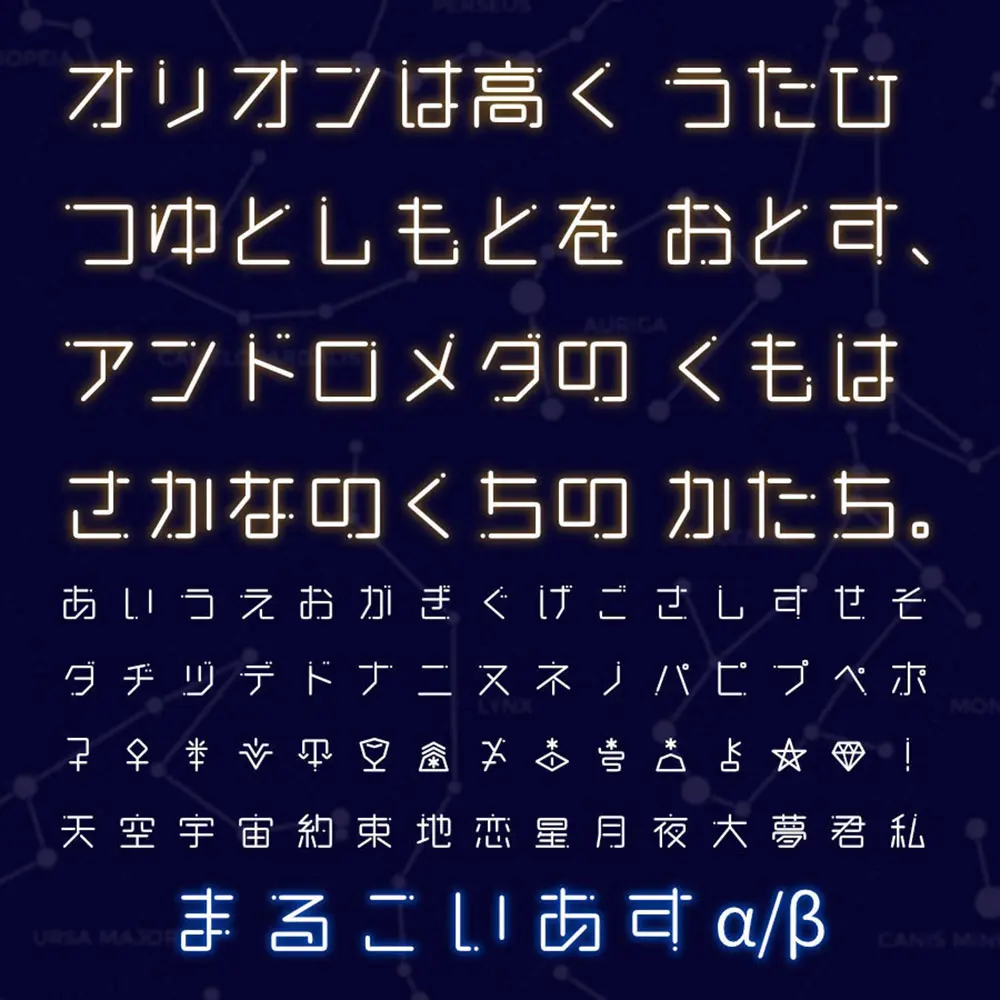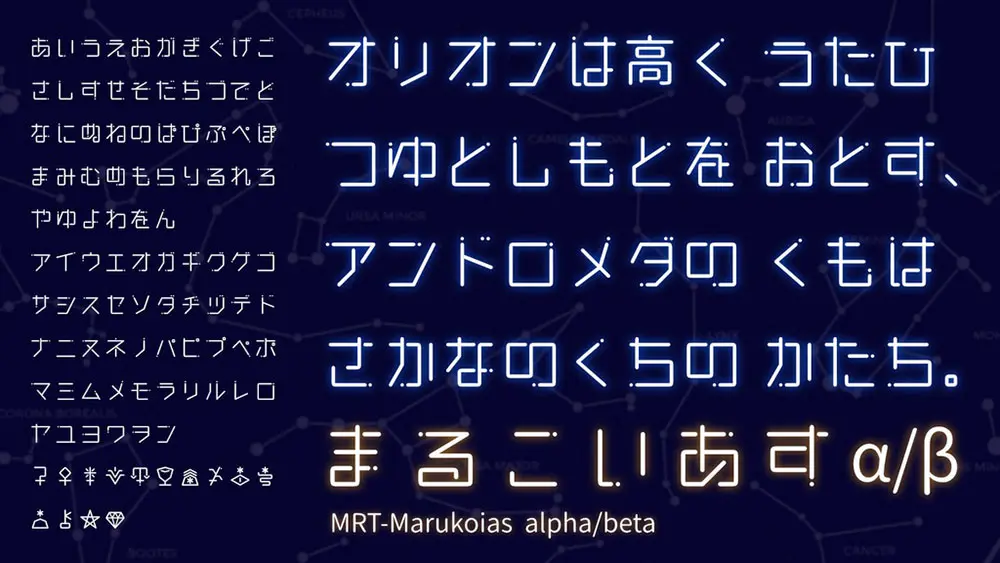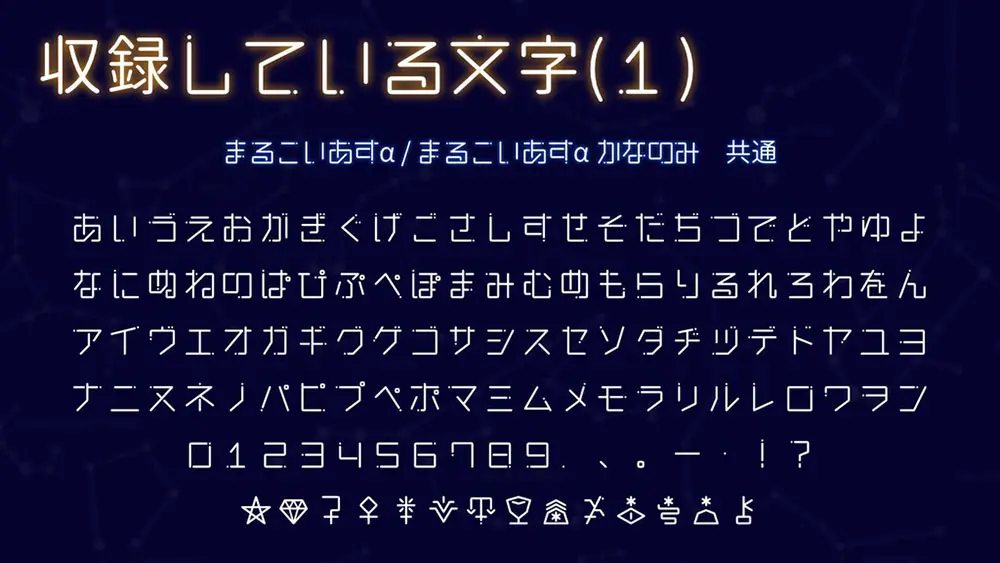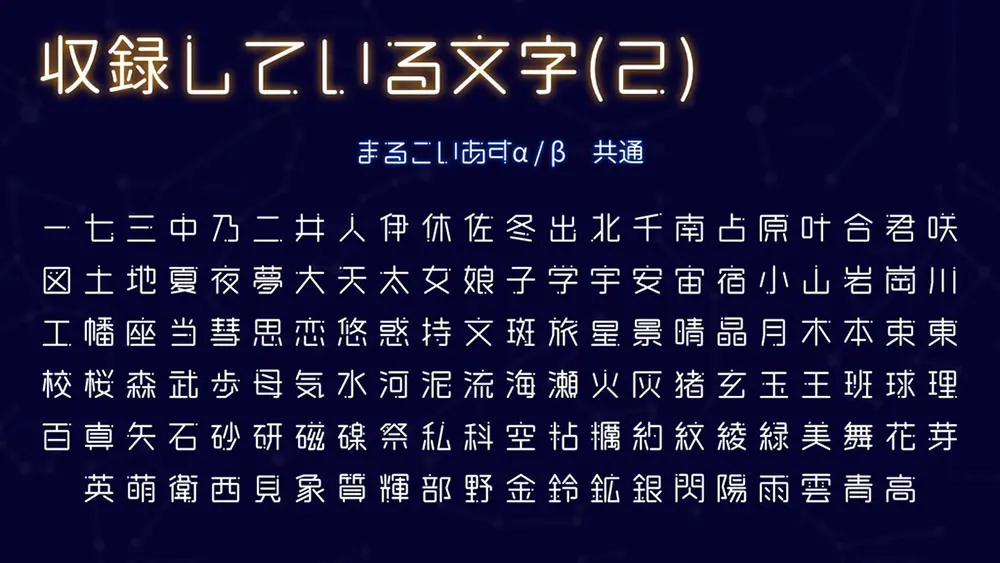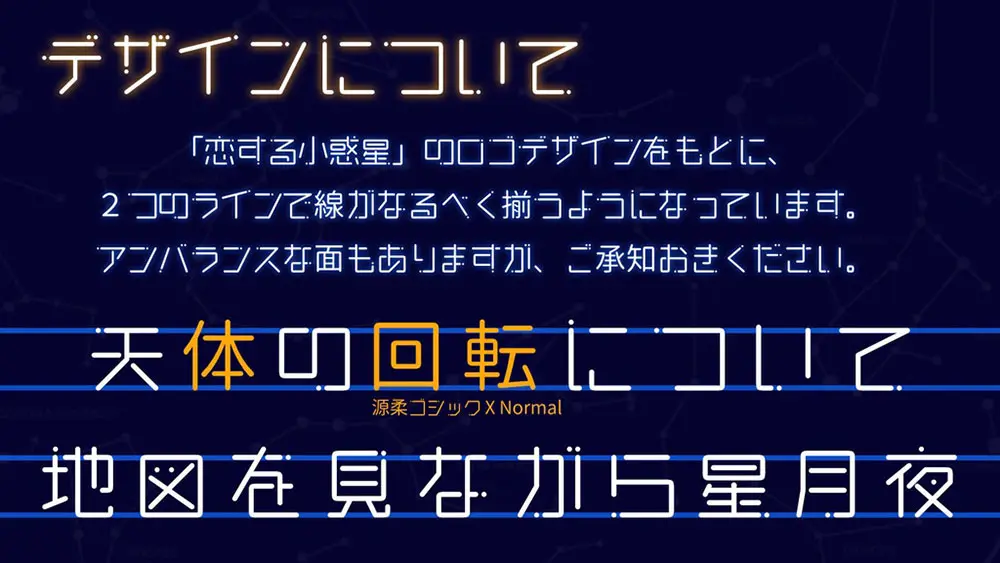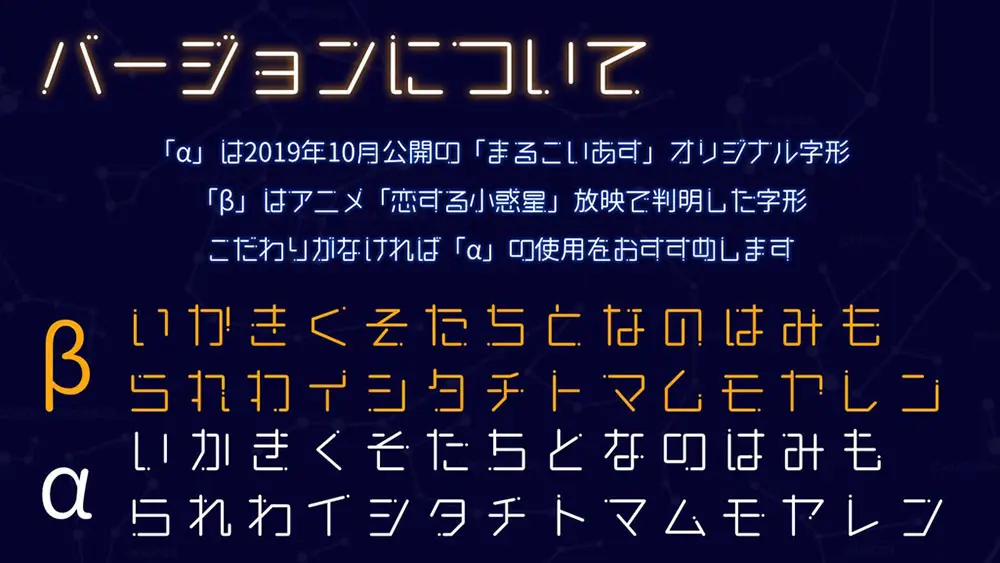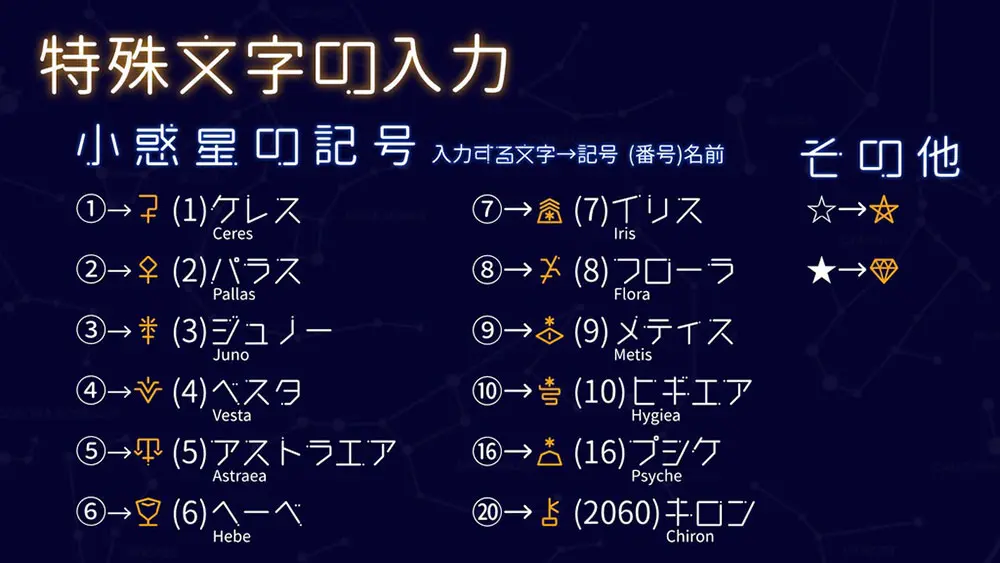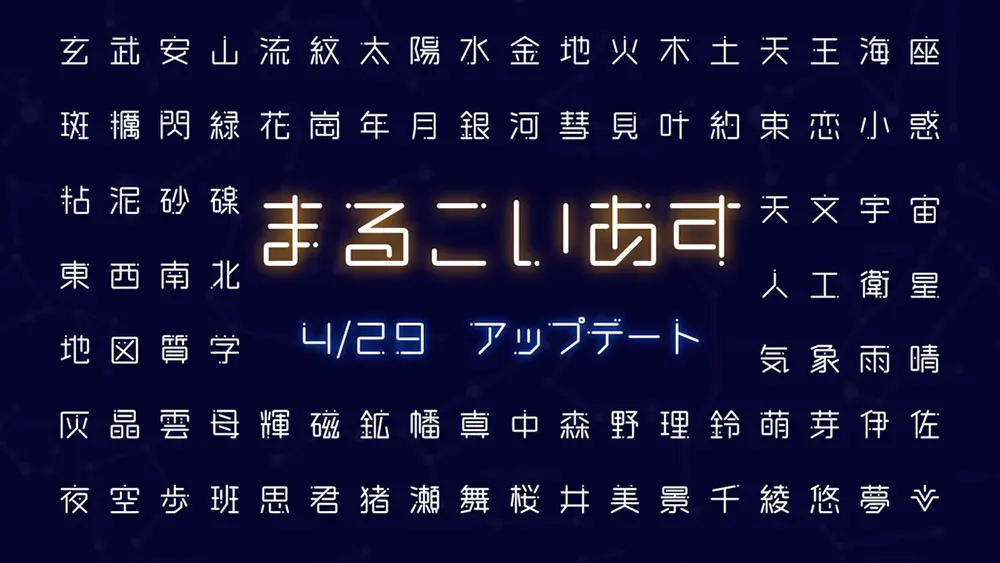
戀星圓體(まるこいあす)是參考漫畫/動畫《戀愛的小行星》的標誌製作的。下邊緣和上邊框對齊,雖然是直線但是有圓形的字體。與“小行星”有關,還收錄了表示小行星的天文符號。
「まるこいあす」は、漫畫/アニメ「戀する小惑星」のロゴを參考して製作しました。下辺と上部で橫線が揃う、直線的だけど丸みのあるフォントです。「小惑星」にちなみ、小惑星を表す天文記號も収録しています。